リバイバルフォント Bentley |
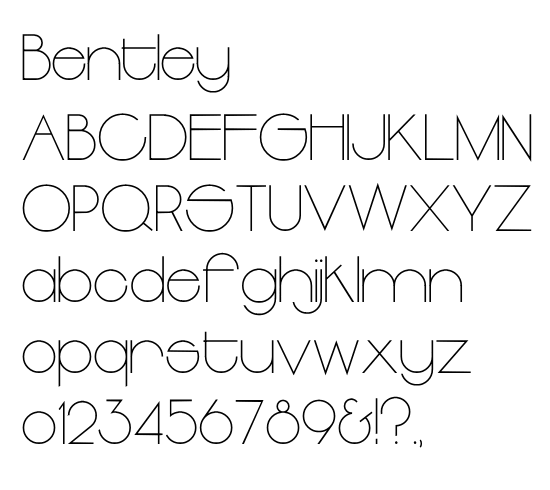
「Bentley」というレア書体を復刻してみた。
Avant Garde Gothic の影響があるようで、小文字のXハイトが高いアールデコ調のジオメトリック書体。
デザイナーやリリース年など詳細は不明ですが、Fotostar 社のカタログに収録されています。
オルタネートもあるので、時間があれば復刻してみようと思ってます。 |
Lubalin, Burns & Co. のレアカタログ |
3月はじめに Lubalin, Burns & Co. のレアカタログをゲット!
本書は1969年に発行された5冊1組のカタログ(1stエディション)で、Lubalin, Burns & Co.
の広告や書体が豊富に収められています。
ただ、期待していた「LSC
Caslon Swash」が掲載されていなかったのが少し残念...。
ルバーリン作品の多くを手掛けたトム・カーネイズ(Tom Carnase)によるフリーハンドのレタリングは圧巻。